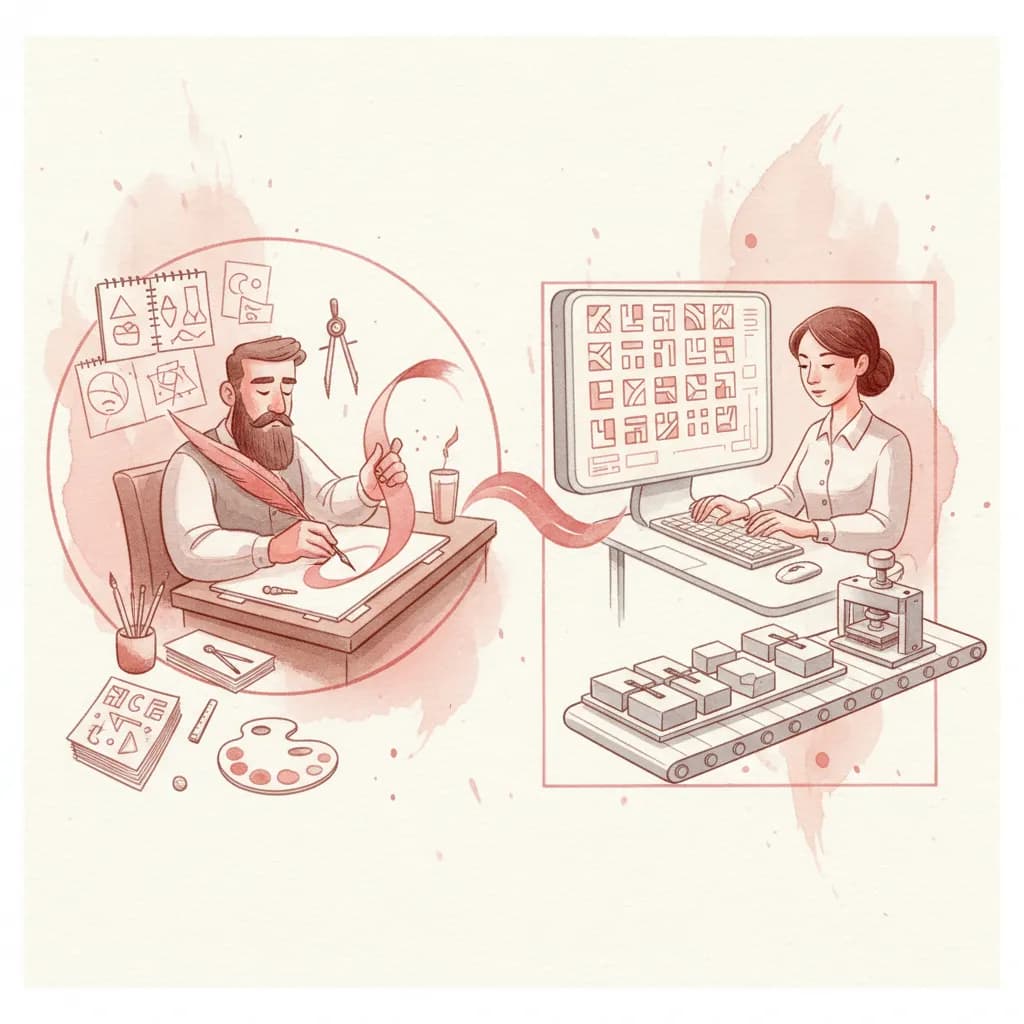
יצירת גופן היא תהליך עיצובי שבו מעצב מפתח מערכת אותיות מקורית, בעלת אופי עקבי, שניתן לשימוש חוזר בפרויקטים שונים. אם תמיד חלמתם לעצב פונט משלכם — בין אם מכתב היד שלכם, מרעיון גרפי טהור, או מצורך מיתוגי — המדריך הזה נועד בדיוק עבורכם. יצירת גופן אינה שמורה למומחים בלבד: עם הכלים הנכונים והתהליך הנכון, כל מעצב גרפי, סטודיו, או אפילו חובב מוטיבציה יכולים להגיע לתוצאה מקצועית.
לפני שמתחילים בתהליך, חשוב להבין הבחנה יסודית: עיצוב אותיות (Lettering) הוא אמנות של ציור ידני של מילים או ביטויים ספציפיים. לעומת זאת, יצירת גופן היא פיתוח מערכת שלמה של תווים — כל האלפבית, ספרות, סימני פיסוק — באופן שמאפשר שימוש חוזר וגמיש בכל טקסט. ההבדל הוא בין יצירת יצירת אמנות חד-פעמית לבין בניית כלי עיצוב שלם.
מעצבים רבים מתחילים מעיצוב אותיות ידני, ואז מבינים שהם רוצים להפוך את הכתב שלהם לפונט שימושי. זה בדיוק המסלול שנסקור כאן. לפרטים על איך טיפוגרפיה מחזקת זהות מותגית, ראו את המאמר כך תיצרו עיצוב גופן ייחודי שמחזק את המותג.
תהליך יצירת גופן מקצועי עובר שישה שלבים עיקריים, החל מהרעיון ועד לקובץ המוכן להפצה. כל שלב בונה על הקודם, ודילוג עליו עלול לפגוע בתוצאה הסופית.
שלב 1: הגדרת אופי וייעוד הפונט
לפני שמציירים אות אחת, שאלו את עצמכם: לאיזה שימוש מיועד הגופן? כותרות? טקסט רץ? מיתוג? פונט לכותרות יכול להרשות לעצמו אופי חזק ודרמטי, בעוד פונט לטקסט רץ חייב להיות קריא גם בגדלים קטנים. הגדירו גם את הטון הרגשי: רשמי, ידידותי, אלגנטי, שובבי?
שלב 2: סקיצות ידניות
המומחים בתחום ממליצים תמיד להתחיל בנייר ועיפרון, לא בתוכנה. צייר את האותיות הבסיסיות תחילה — בעברית מקובל להתחיל מ-א, ב, ג ומהאות ו כדי לבסס את השפה הגרפית. שימו לב לעובי הקווים, לפינות, ולאופן שבו האות "יושבת" בחלל.
שלב 3: דיגיטציה של האותיות
יש שתי דרכים עיקריות: סריקת הסקיצות הידניות ועריכתן בתוכנה, או עיצוב ישיר בתוכנה וקטורית. לשיטת הסריקה, ניתן להשתמש בכלים מקוונים כמו Calligraphr — שבו בוחרים שפה (מומלץ לבחור גם עברית וגם אנגלית), מדפיסים תבנית, ממלאים את האותיות ידנית, וסורקים בחזרה. לעיצוב מקצועי יותר, Adobe Illustrator מאפשר ליצור אותיות בהתאמה אישית בדיוק גבוה.
שלב 4: בניית הפונט בתוכנת פונטים
לאחר שהאותיות מוכנות כוקטורים, מייבאים אותן לתוכנת פונטים ייעודית. בשלב זה מגדירים את ה-metrics: גובה האות, קו הבסיס, גובה האותיות הגדולות, ורווחים בין אותיות (Kerning). כשסיימתם לערוך, לוחצים על "Build Font", נותנים שם לפונט, ולוחצים שוב על Build.
שלב 5: בדיקה ועריכה
מתקינים את הפונט ובודקים אותו בהקשרים שונים — כותרות, גוף טקסט, גדלים קטנים וגדולים. שימו לב לצמדי אותיות בעייתיים ולרווחים לא אחידים. שלב זה חוזר על עצמו מספר פעמים עד שהתוצאה משביעת רצון.
שלב 6: ייצוא ורישוי
מעצבים רבים שמתחילים את תהליך יצירת גופן לראשונה נתקלים באותן מלכודות. הכרת הטעויות מראש חוסכת שעות עבודה ואכזבות.
לפי מומחים בתחום הטיפוגרפיה, יצירת גופן עברי מוצלח מחייבת הבנה של המאפיינים הייחודיים של האלפבית העברי — כולל אותיות סופיות, אפשרות לניקוד, וכיוון הכתיבה מימין לשמאל. לעיון בעקרונות בחירת פונטים לעברית, ראו עיצוב טקסט בעברית – איך לבחור את הפונט הנכון?
לאחר שהבנתם את השלבים והמלכודות, הנה כמה עצות שיחסכו לכם זמן ויעלו את רמת התוצאה בתהליך יצירת גופן:
אם אתם מחפשים השראה לפני שמתחילים ביצירת גופן משלכם, כדאי לבחון פונטים עבריים מקצועיים כדוגמת פונט מנדולינה — שמשלב אלגנטיות מובנית עם תנועה מודרנית — כדי להבין מה מאפיין פונט בעל נוכחות ועקביות. כמו כן, ניתן להתרשם מ-פונט ז'ולייט כדוגמה לפונט סקריפט שמצליח לשמור על אופי חזק לאורך כל מערכת האותיות.
תלוי ברמת המורכבות ובניסיון המעצב. פונט מכתב יד פשוט עם 27 אותיות עבריות בלבד יכול להיות מוכן תוך ימים אחדים. פונט מקצועי מלא עם אותיות סופיות, ניקוד, ספרות וסימנים מיוחדים — יכול לקחת שבועות עד חודשים של עבודה. מומלץ להתחיל בגרסה מינימלית ולהרחיב בהדרגה.
כן, ישנם הבדלים משמעותיים. האלפבית העברי כולל 27 תווים (כולל אותיות סופיות), כתיבה מימין לשמאל, ואפשרות לניקוד שמוסיף שכבת מורכבות. בנוסף, לא כל תוכנות הפונטים תומכות בצורה מלאה בעברית, ולכן חשוב לבחור כלי שמאפשר הגדרת כיוון RTL וטיפול נכון בצורות האותיות.
למתחילים, Calligraphr הוא הכלי הנגיש ביותר — עובד דרך הדפדפן, ללא הורדת תוכנה, ומאפשר יצירת פונט מכתב יד בחינם. מי שרוצה לעבור לשלב הבא יכול לנסות תוכנות ייעודיות ליצירת פונטים מקצועיות. Adobe Illustrator מתאים לשלב עיצוב הוקטורים לפני הייבוא לתוכנת פונטים.
לגלרייה המלאה של הפונטים ←יצירת גופן מותאם אישית היא אחד הפרויקטים המספקים ביותר עבור מעצבים — היא מאחדת אמנות, עיצוב, ולוגיקה טכנית לכדי כלי שאפשר להשתמש בו שוב ושוב. ששת השלבים שסקרנו — הגדרת אופי, סקיצות ידניות, דיגיטציה, בנייה בתוכנה, בדיקה, וייצוא — הם מפת הדרכים שתוביל אתכם מרעיון לפונט מוכן.
הצעד הבא שלכם: התחילו עם 5 אותיות בלבד, בדקו שהן מדברות באותה שפה גרפית, ורק אז המשיכו לשאר האלפבית. יצירת גופן מקצועי לא דורשת שלמות מיידית — היא דורשת סבלנות, עקביות, ונכונות לחזור ולשפר. המתחילים ביצירת גופן עברי ייחודי ימצאו ב-Google Fonts מאגר השוואה טוב לניתוח מה מאפיין פונטים מקצועיים מוצלחים.